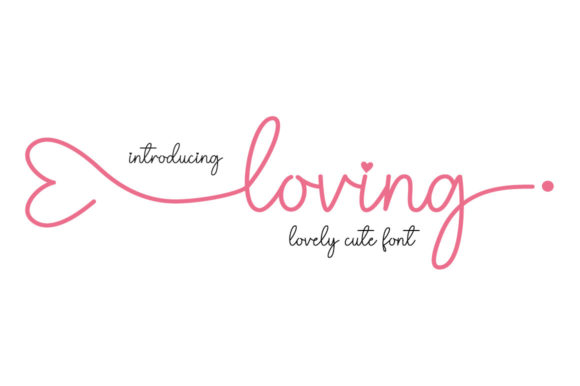
Loving Font
Loving Font – A Fonte Script Que Transforma Seu Projeto em Elegância
Se você está em busca de uma tipografia que una delicadeza, sofisticação e modernidade, a Loving Font chegou para ser a escolha perfeita. Desenvolvida com traços finos e curvas suaves, essa fonte script se destaca em logos, branding, convites, papelaria, designs de casamento, postagens em redes sociais e muito mais. Além de seu visual impecável, o recurso PUA encoded permite acesso fácil a todos os glifos e swashes, garantindo total liberdade criativa.
Principais Características da Loving Font
- Design elegante e contemporâneo – combina o charme clássico das fontes cursivas com um toque moderno.
- Versatilidade de uso – ideal para identidade visual, convites de casamento, cartões de visita, banners digitais e impressos.
- Glyphs e swashes completos – a codificação PUA oferece acesso a variações ornamentais sem complicações.
- Alta legibilidade – mesmo em tamanhos menores, as linhas finas mantêm clareza e elegância.
Por Que a Loving Font é a Melhor Opção para Seu Projeto?
Ao escolher a Loving Font, você garante um visual premium que se destaca da concorrência. Sua estética refinada cria uma conexão emocional imediata com o público, tornando cada mensagem mais memorável. Seja para um convite de casamento íntimo ou para a identidade visual de uma marca de luxo, a Loving entrega o impacto visual que você precisa.
Dicas de Aplicação para Maximizar o Impacto
- Use swashes nas iniciais de nomes ou títulos para um toque artístico exclusivo.
- Combine a Loving com uma fonte sans‑serif neutra para equilibrar elegância e legibilidade em textos longos.
- Aplique a fonte em cores pastel ou douradas para reforçar o clima romântico e sofisticado.
- Experimente efeitos de sombra suave em mídias digitais para realçar a delicadeza dos traços.
Em resumo, a Loving Font é mais que uma simples tipografia script – é uma ferramenta de storytelling visual que eleva qualquer projeto a um patamar de elegância e classe. Seu conjunto completo de glifos e swashes, aliado ao design atemporal, faz dela a escolha ideal para designers que desejam criar peças inesquecíveis. Não perca a oportunidade de transformar sua comunicação visual com a sofisticação que só a Loving pode oferecer.